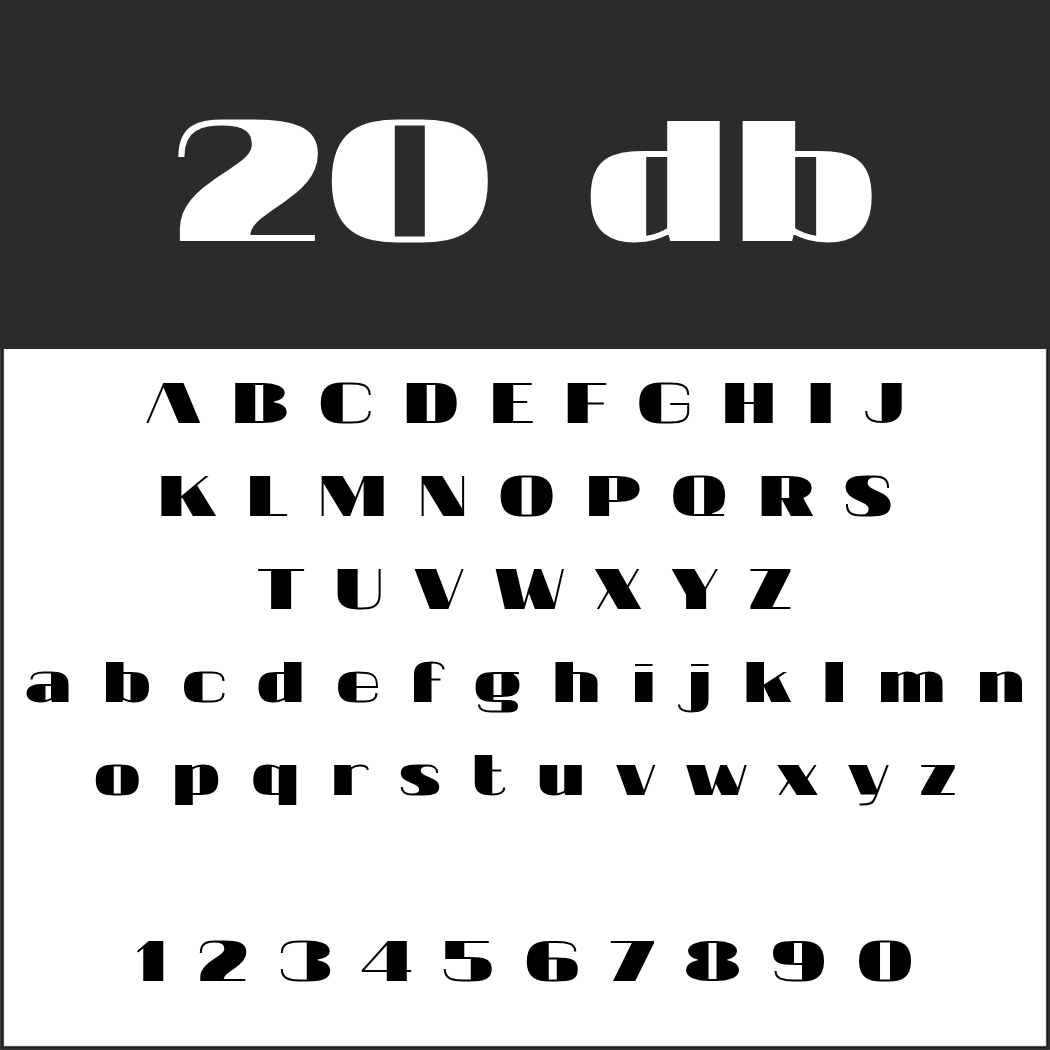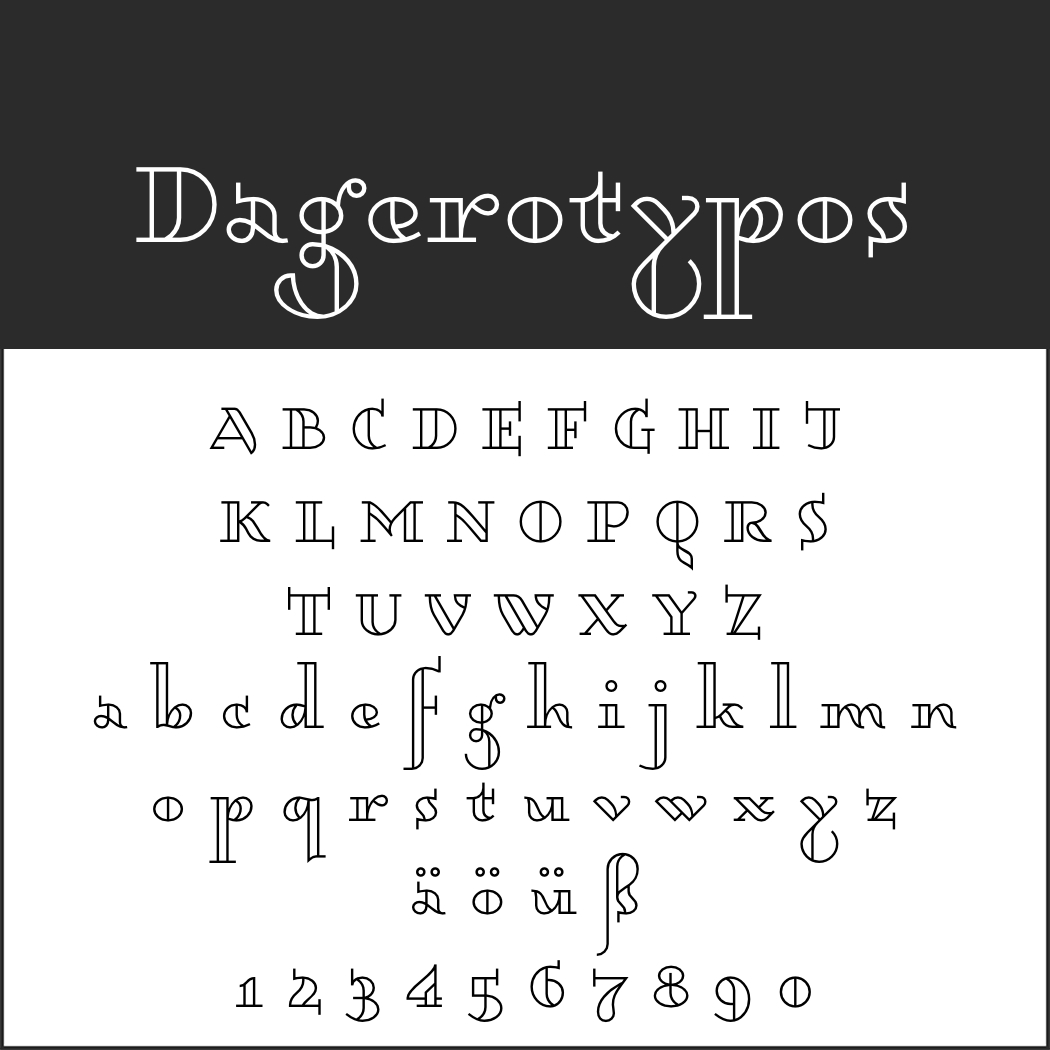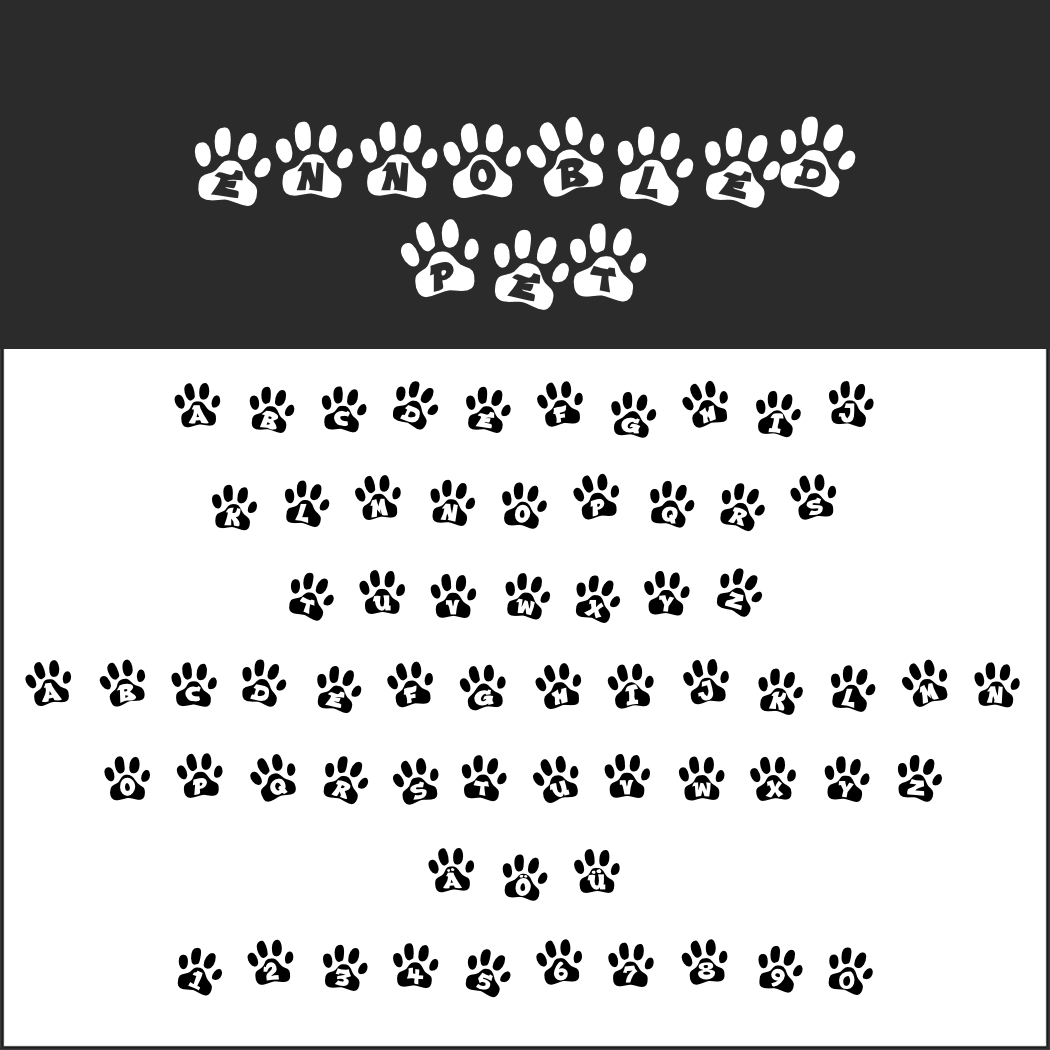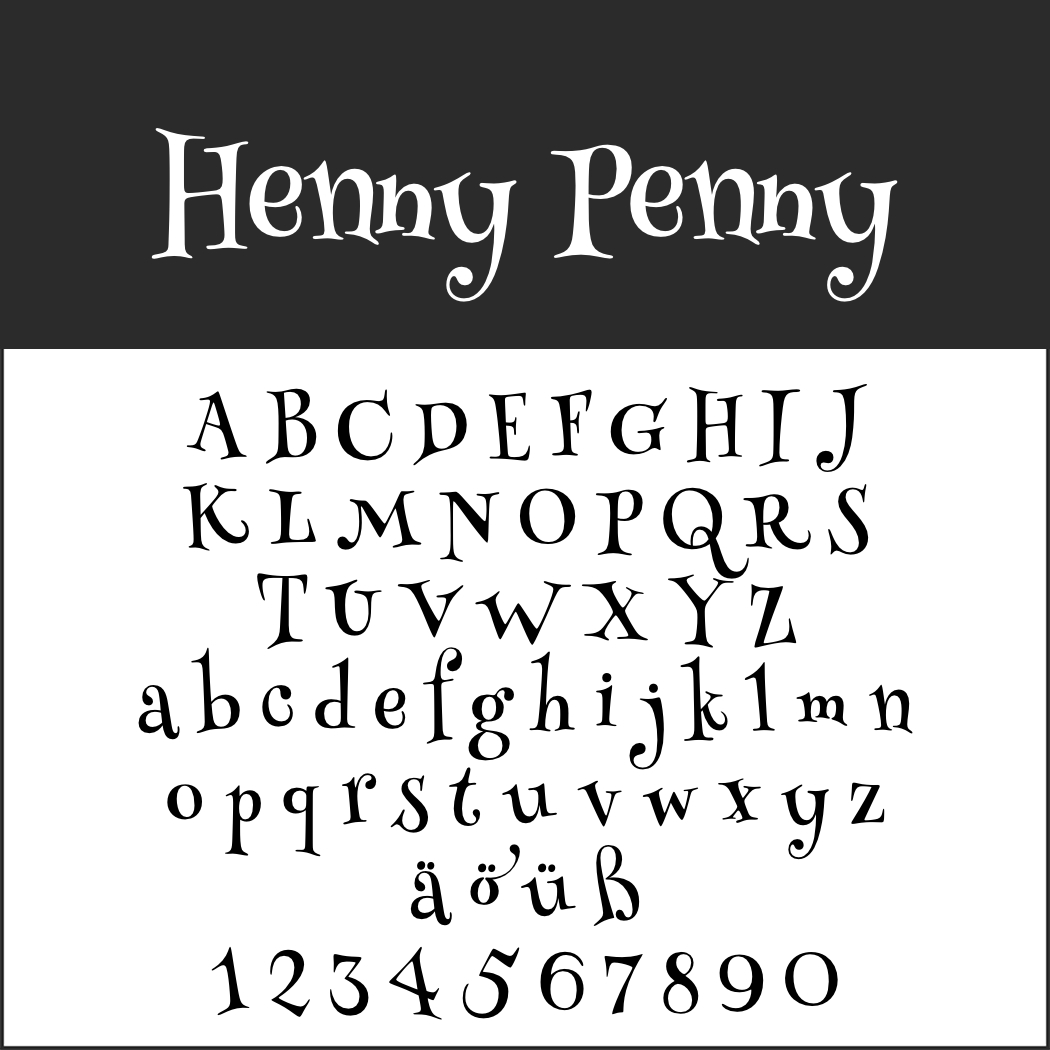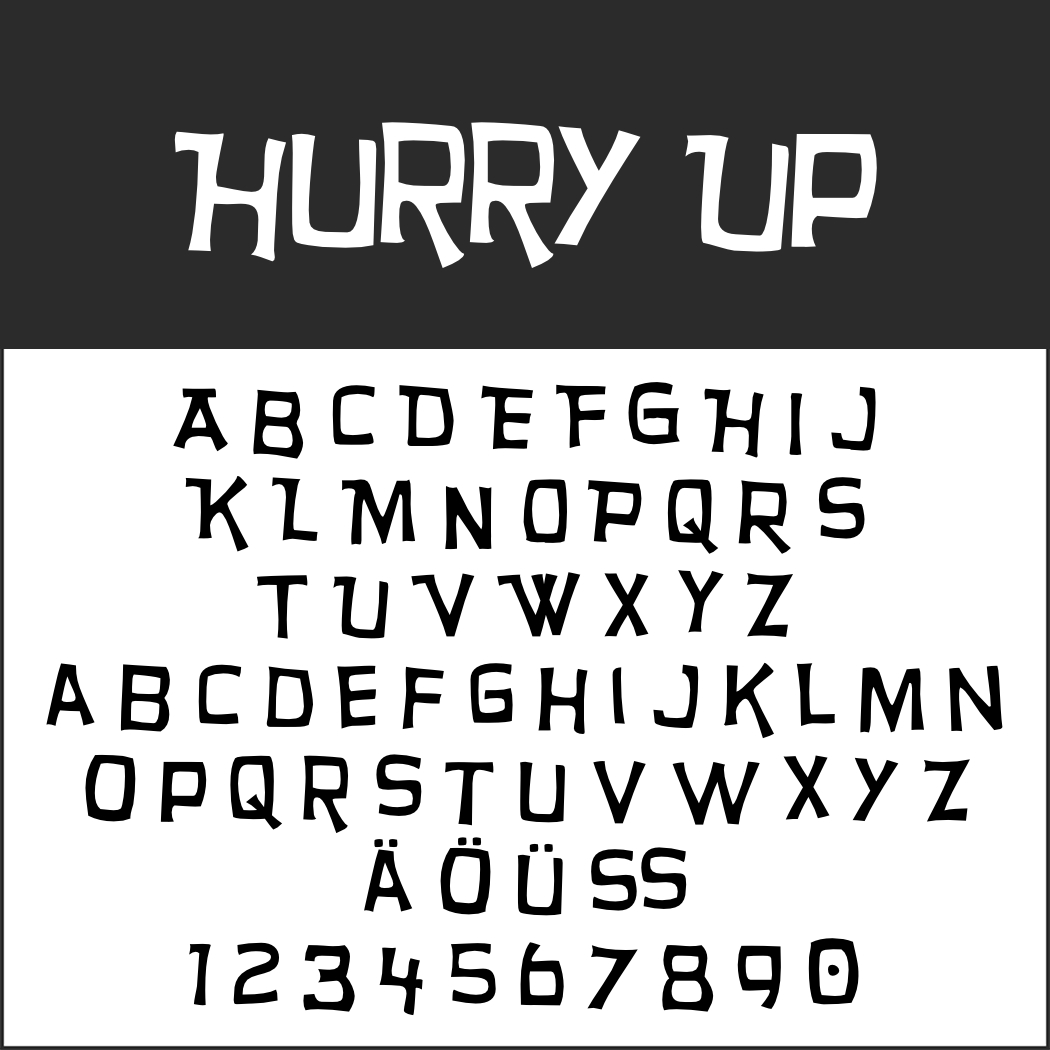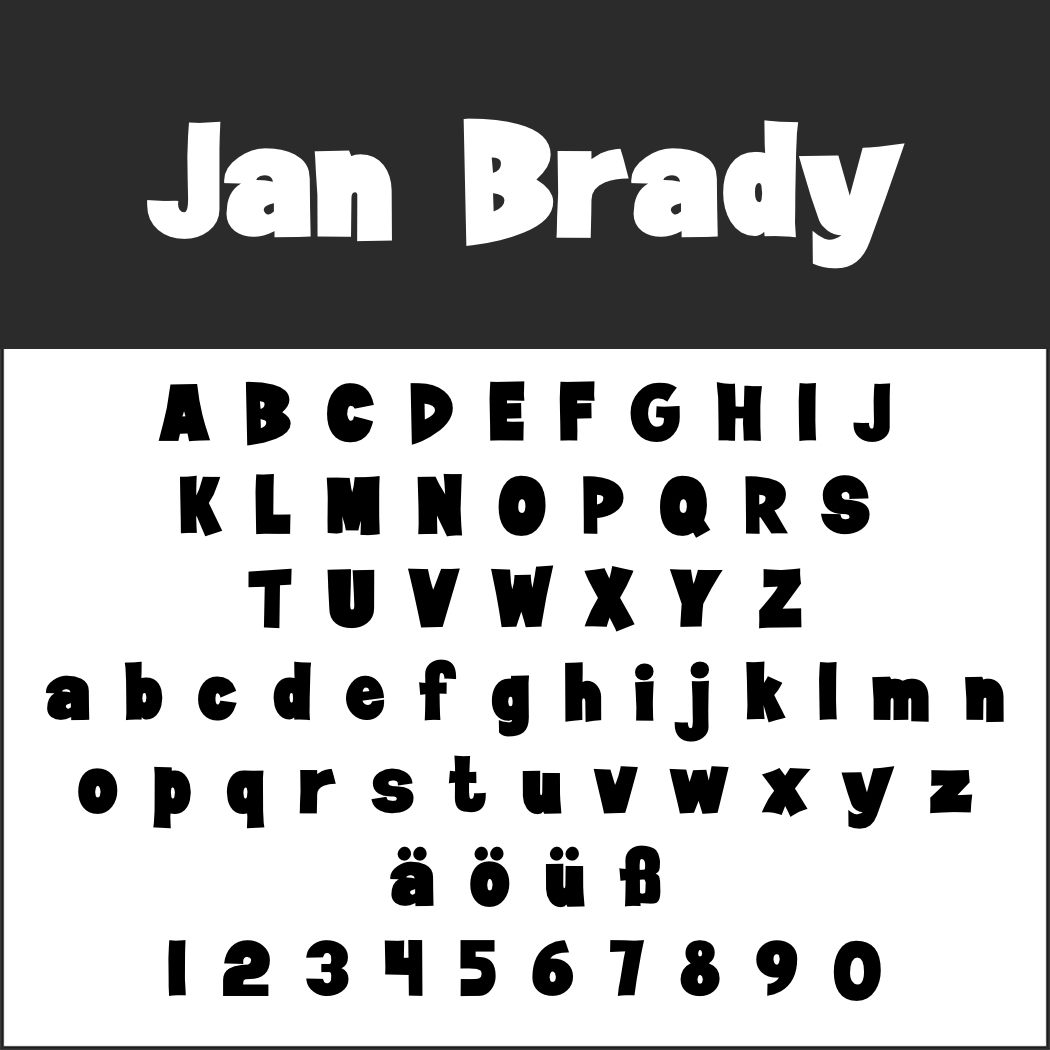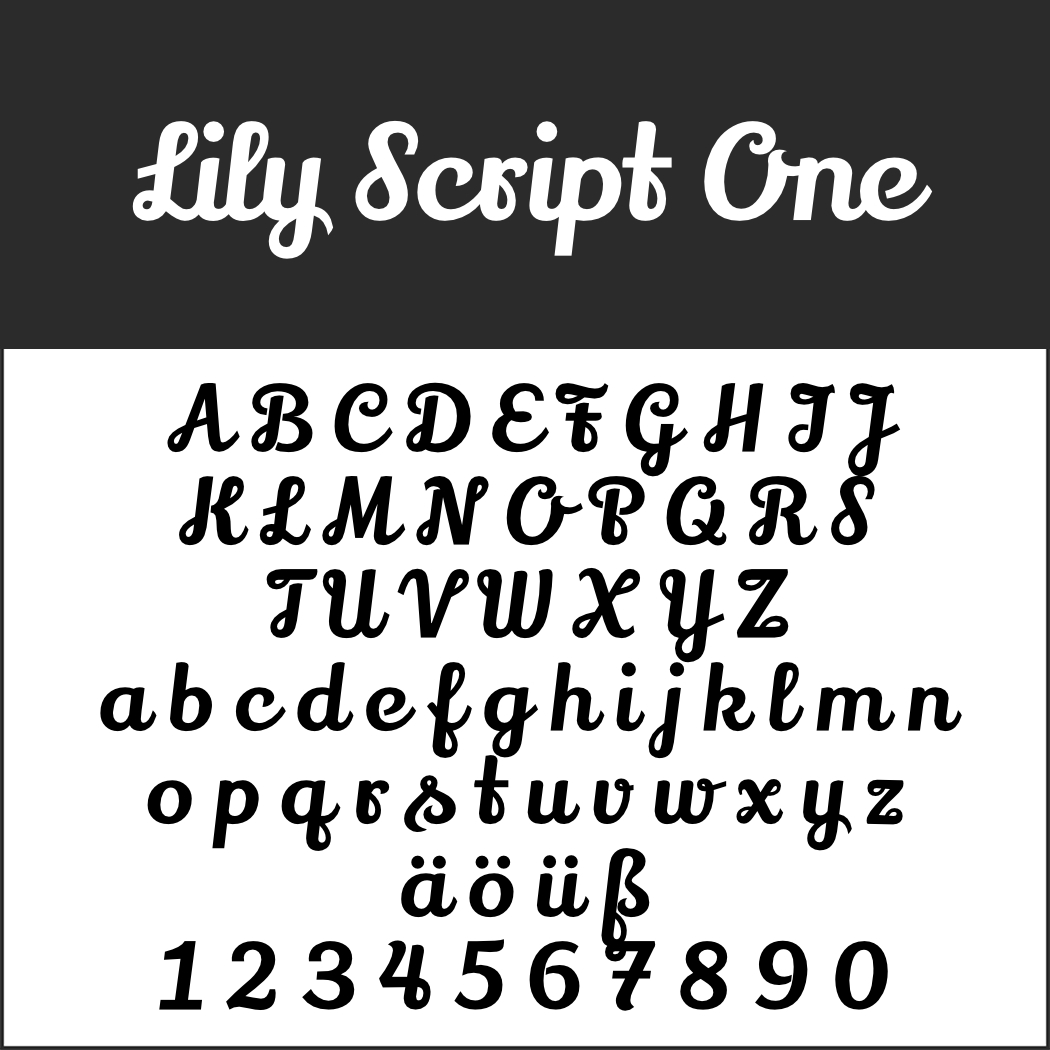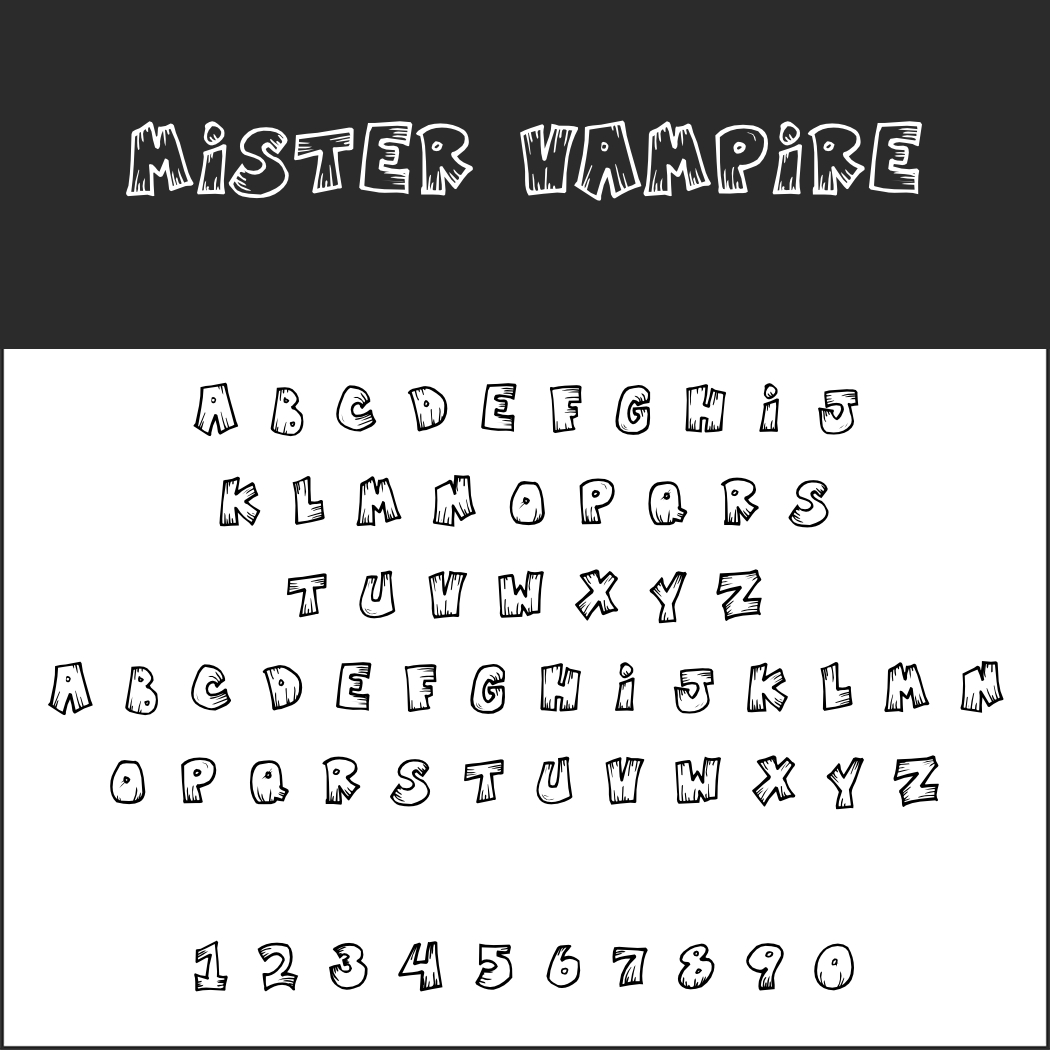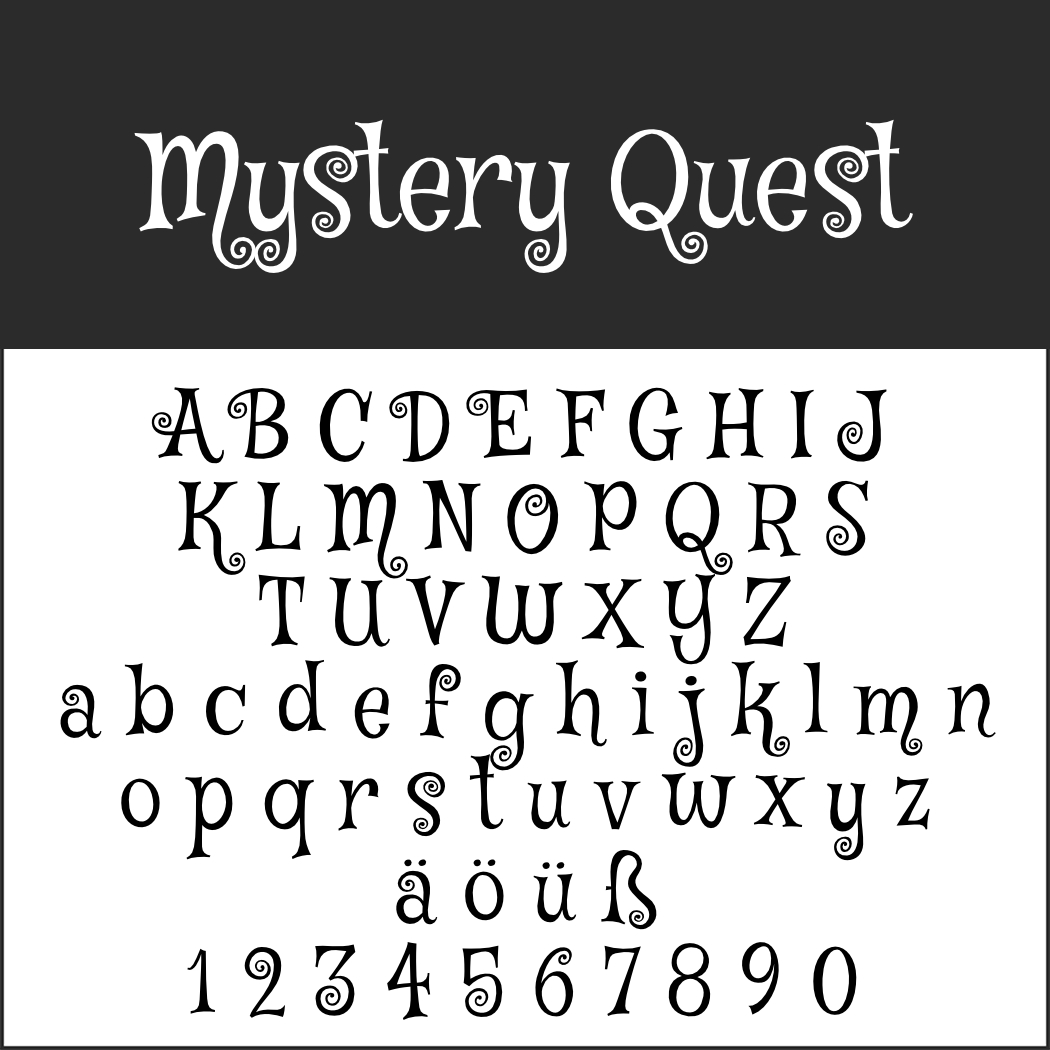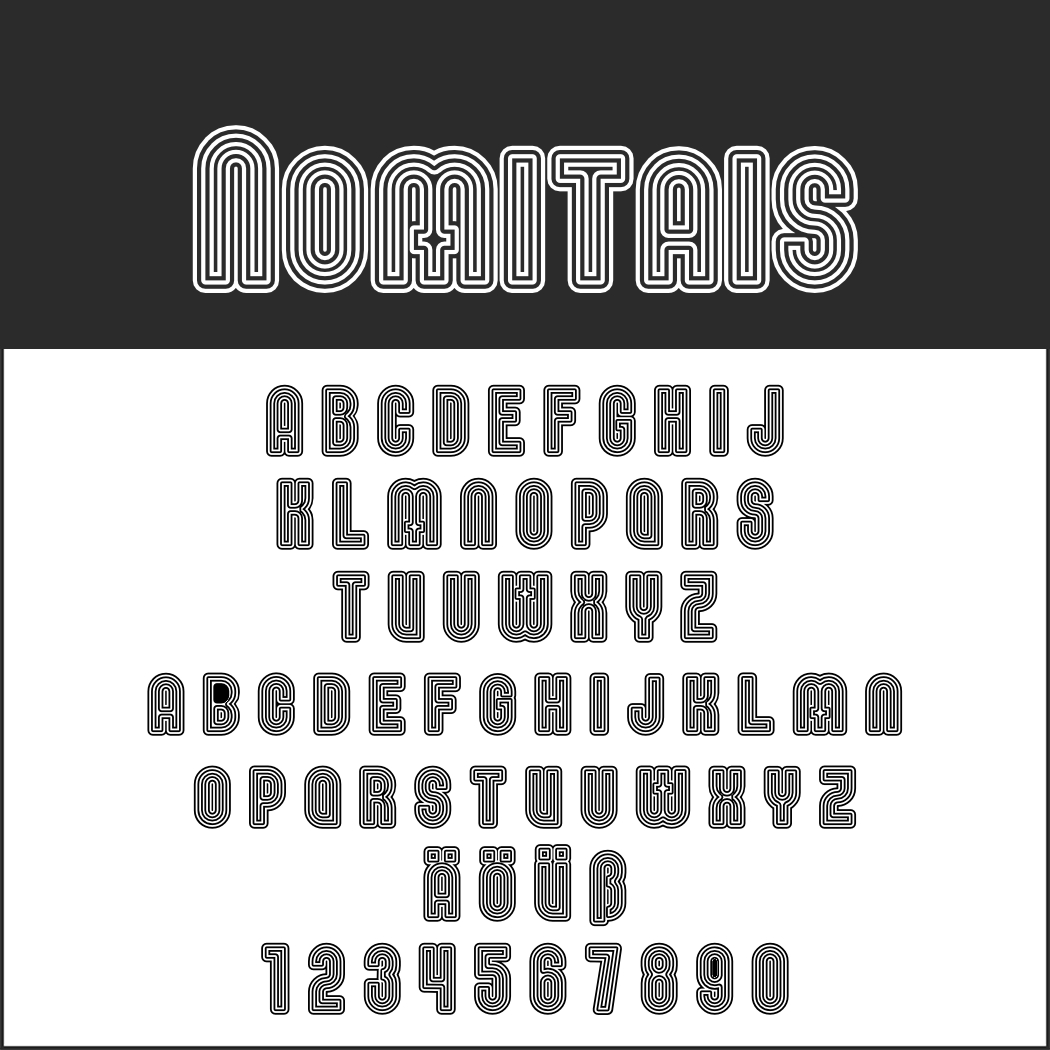
Wodurch zeichnen sich lustige Schriftarten aus? Da gehen die Meinungen vermutlich sehr weit auseinander. Festhalten lässt sich allerdings, dass es ganz erheblich auf den Zusammenhang ankommt. Selten ist eine Schriftart für sich allein genommen witzig. Kombiniert man sie jedoch entsprechend, kann sie ihre heitere Wirkung voll entfalten.
Wir haben uns also auf die Suche nach Gratis-Fonts gemacht, die zu leichteren Themen passen. In unserer Auswahl finden sich daher Schriftarten mit Comic-Anleihen, 3D-Buchstaben, welche mit Retro-Charme und solche, die ein bisschen aus der Reihe tanzen. Sollte nicht das Passende dabei sein: Am Ende verlinken wir auf weitere Fonts-Sammlungen, die ähnliche Schriftarten bieten.
Wir haben einiges an Fonts zusammengetragen, was für nicht ganz so ernste Themen geeignet sein kann.
Verspielte lustige Schriftarten
Ennobled Pet
Jeder Buchstabe befindet sich in einer Pfote, deren Gestaltung an Stempeldruck erinnert. Der passende Font für alles Animalische und tierisch Gute.
- Besonderheit: keine Kleinbuchstaben, kein ß
- Design: Raymond Larabie (https://typodermicfonts.com/)
Lily Script One
Eine schöne Schreibschrift, die sich für Überschriften und kurze Fließtexte eignet. Praktisch ist Lily Script One zudem, wenn man etwas Platz schinden muss.
- Design: Julia Petretta
Henny Penny
Henny Penny ist die Heldin einer Volkserzählung und diverser Bilderbücher. Der gleichnamige Font setzt dem berühmten Huhn ein liebevolles Denkmal.
- Design: Brownfox (https://brownfox.org/)
Retro und Nostalgie
20 db
Art déco mit extremen Kontrasten: An Schlagzeilen und Überschriften in 20 db sieht man so leicht nicht vorbei.
- Besonderheit: keine deutschen Sonderzeichen
- Design: Jovanny Lemonad (https://typetype.org/freefonts/)
Dagerotypos
Auch bei Dagerotypus finden wir Art-déco-Anleihen. Mehr Fonts in diesem Stil finden Sie unter Art déco Schriftart mit mondänem Charme.
- Design: gluk (http://www.glukfonts.pl/)
Mystery Quest
Ein bisschen verspielt, ein bisschen Hippie. Mystery Quest ist von der Flowerpower inspiriert.
- Design: Font Diner (https://fontdiner.com/)
Rum Raisin
Die Designer haben sich für diesen Font an der Schrift auf einer alten Müslischachtel von Kelloggs bedient. Rosinen dürften tatsächlich drin gewesen sein, Rum eher nicht.
- Design: Astigmatic One Eye Typographic Institute
Nomitais
Der Designer entwickelte für diesen Font mit 60er-Jahre-Flair aus einer Outline-Schrift eine weitere – Outline im doppelten Sinne also. Nur was für eher kurze Schlagwörter.
- Besonderheit: keine Kleinbuchstaben
- Design: Peter Wiegel (http://www.peter-wiegel.de/)
Comic-Schriftarten
Hurry Up
Cartoon-Schrift im Stil der 1960er. Kann auch als Vorlage dienen, wenn die Buchstaben ausgeschnitten werden sollen.
- Besonderheit: keine Kleinbuchstaben
- Design: Raymond Larabie (https://typodermicfonts.com/)
Yellow Swamp
Der Comic-Font ist eine Hommage an die Kleinstadt Mandeville in Louisiana. Dem Empfinden des Designers nach ist dort alles gelb. Folgerichtig benannte der seine Schriftart „Gelber Sumpf“.
- Besonderheit: keine Großbuchstaben, keine deutschen Sonderzeichen
- Design: Divide By Zero (http://fonts.tom7.com/)